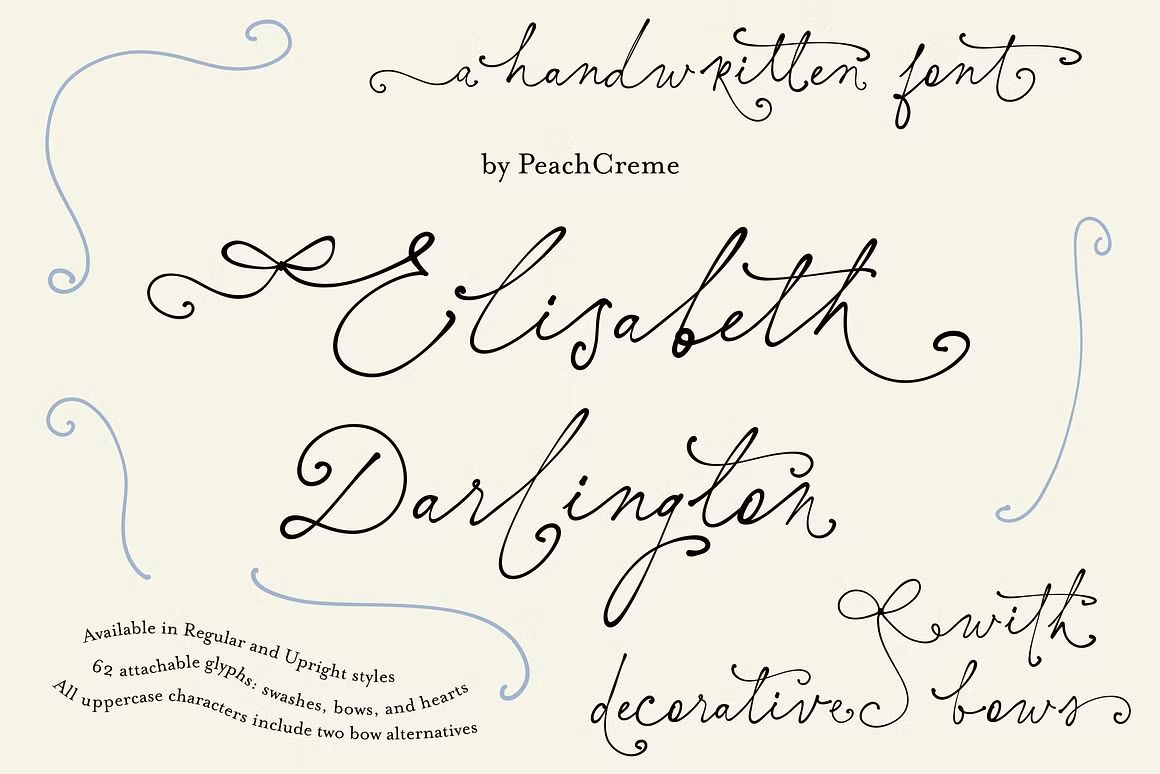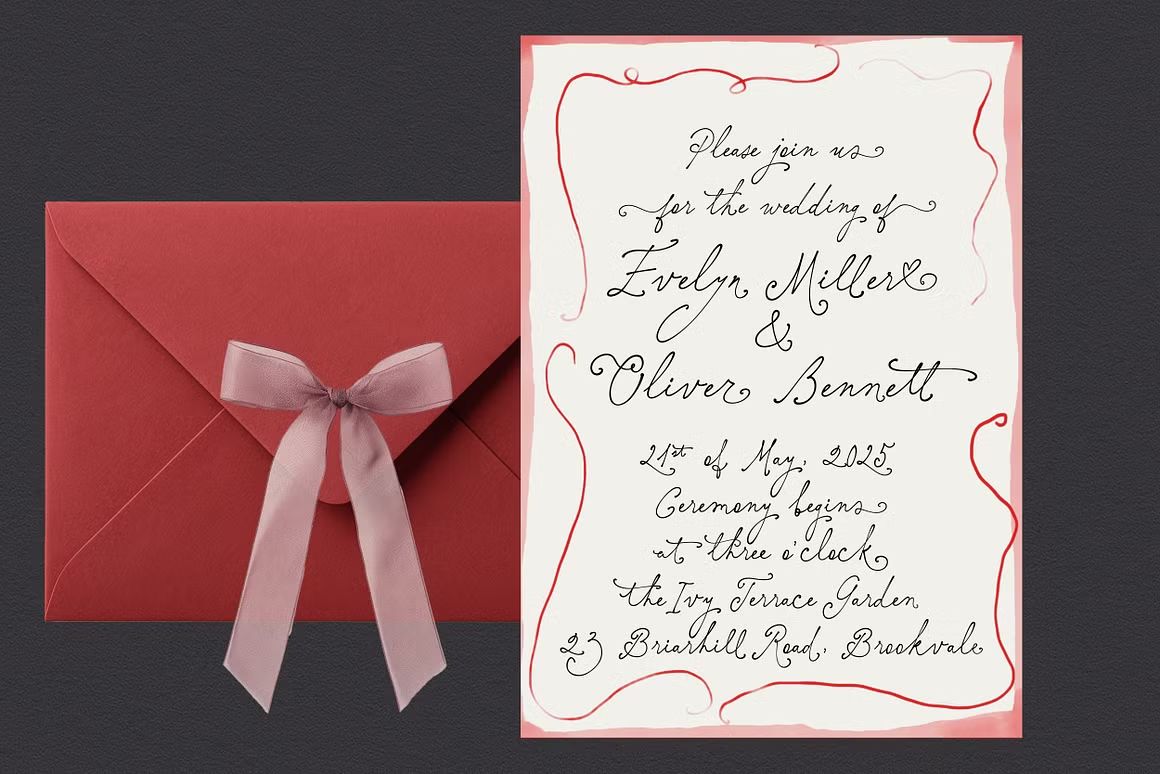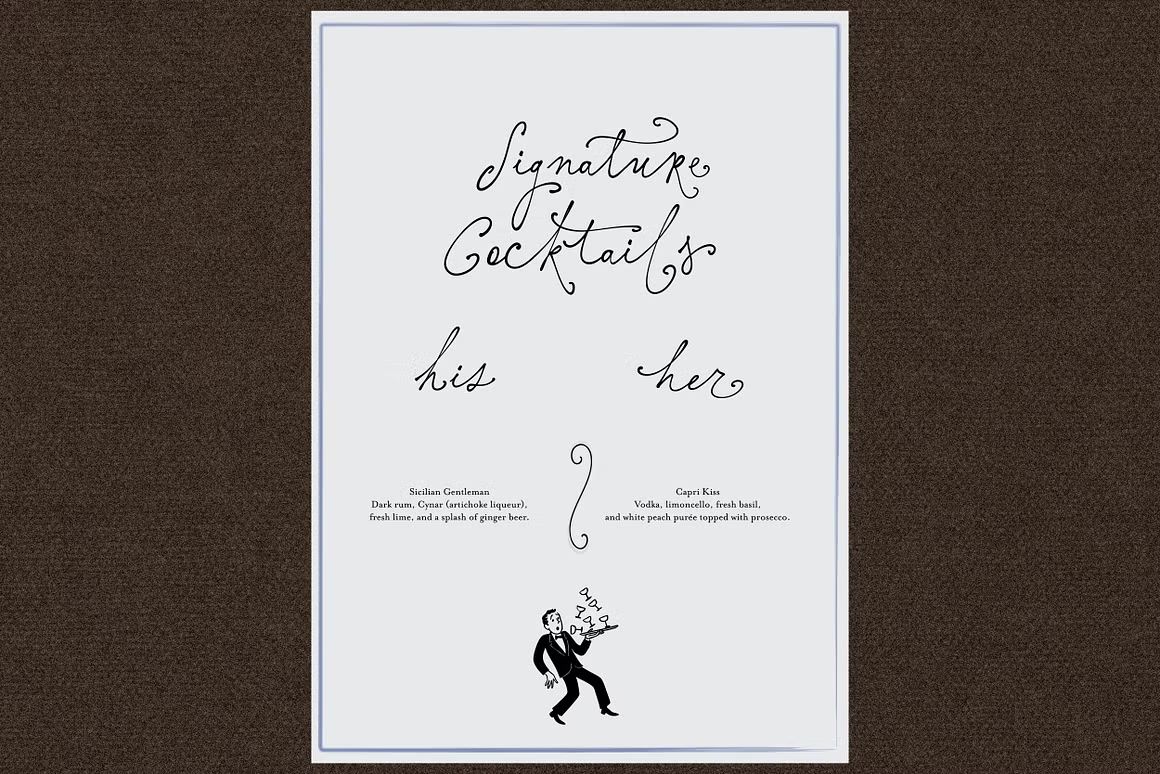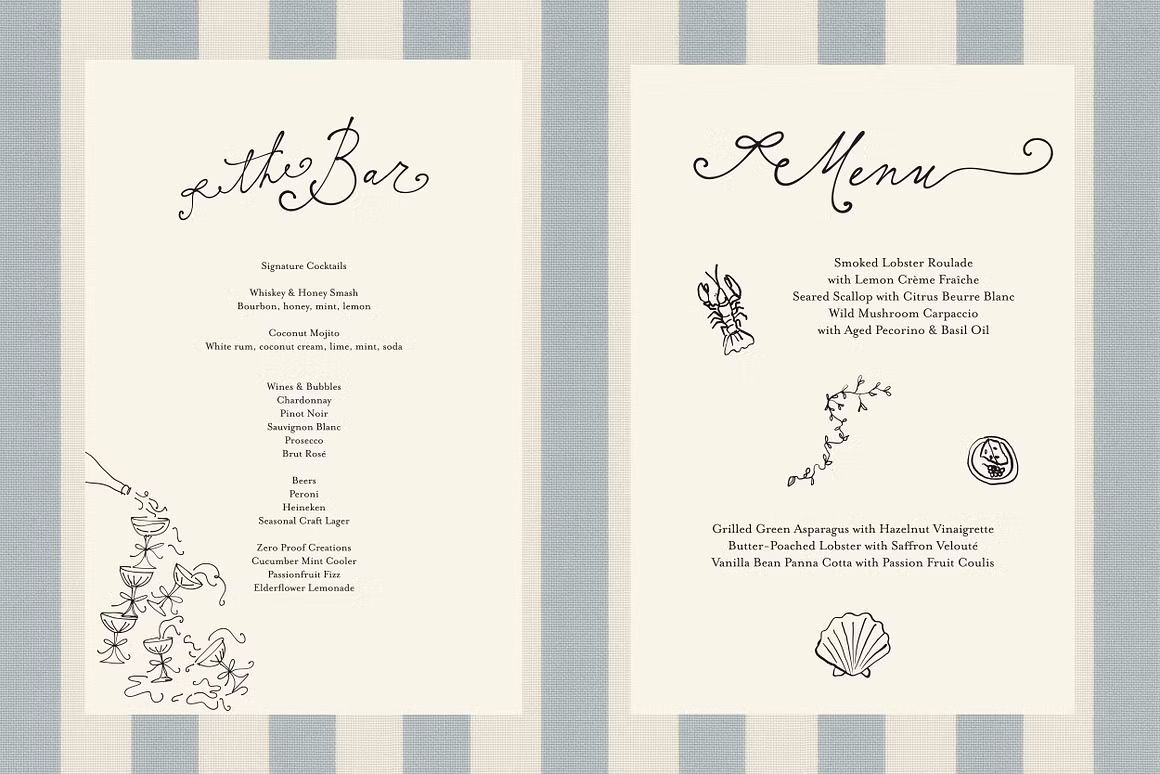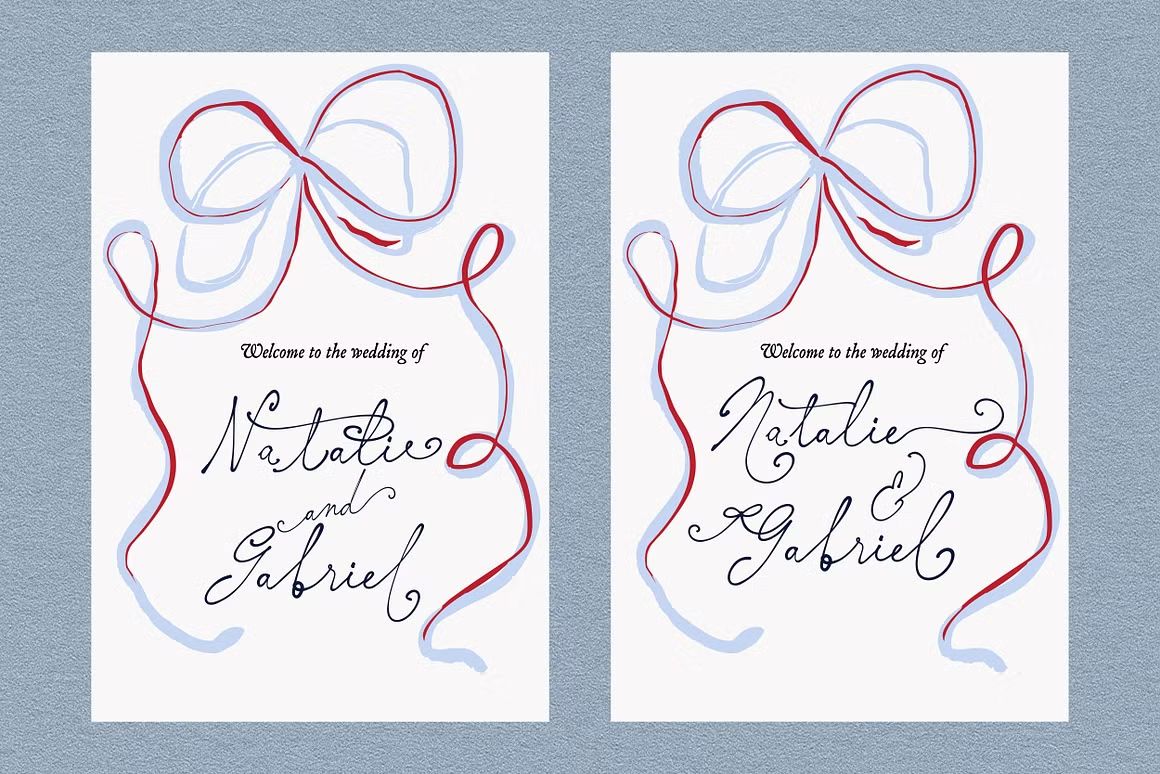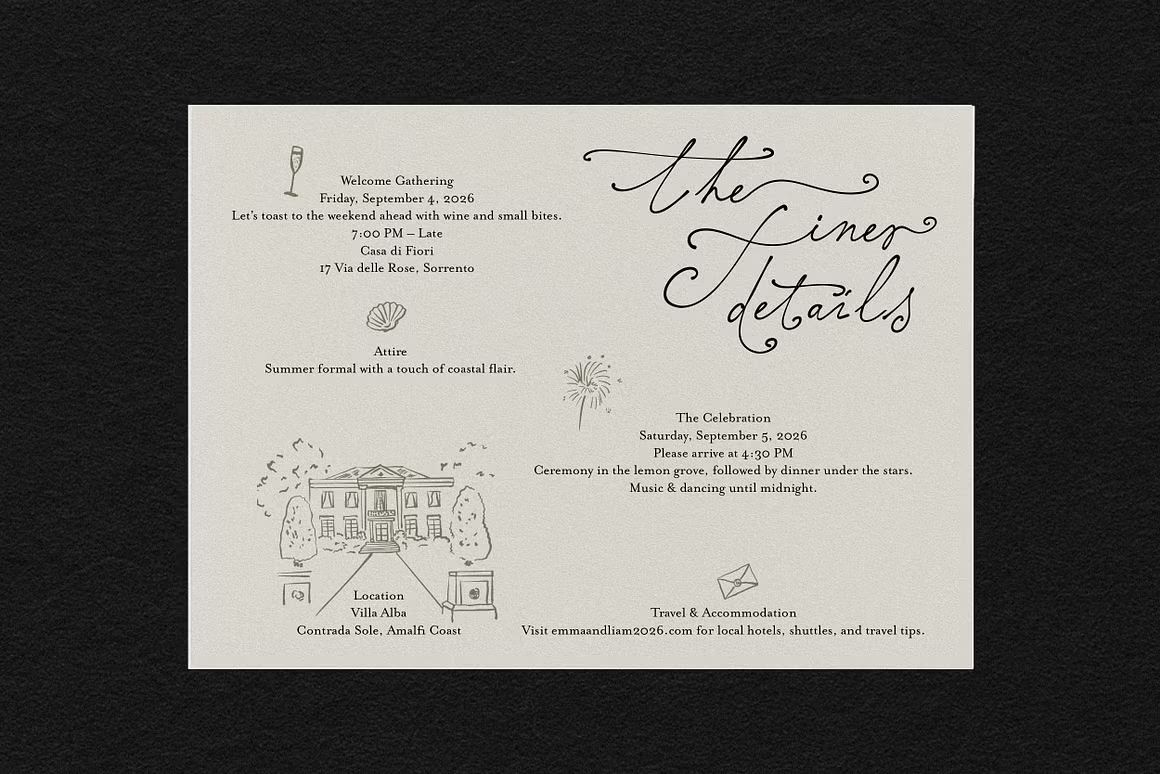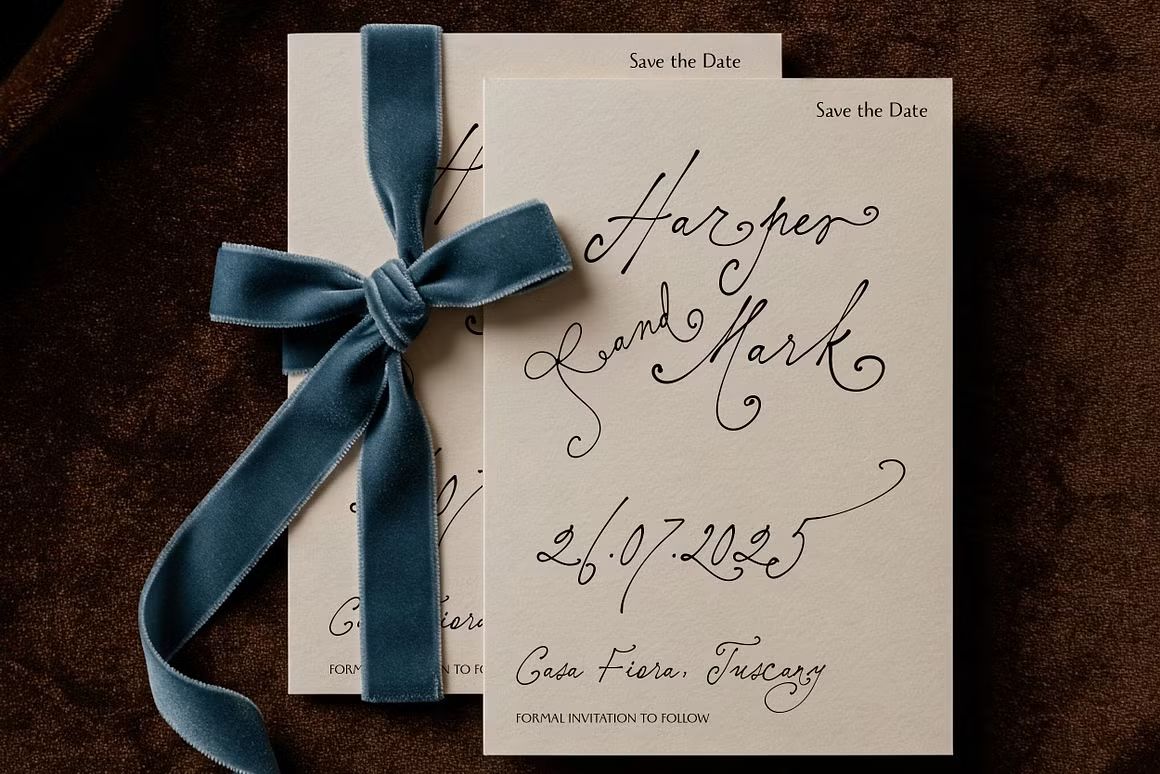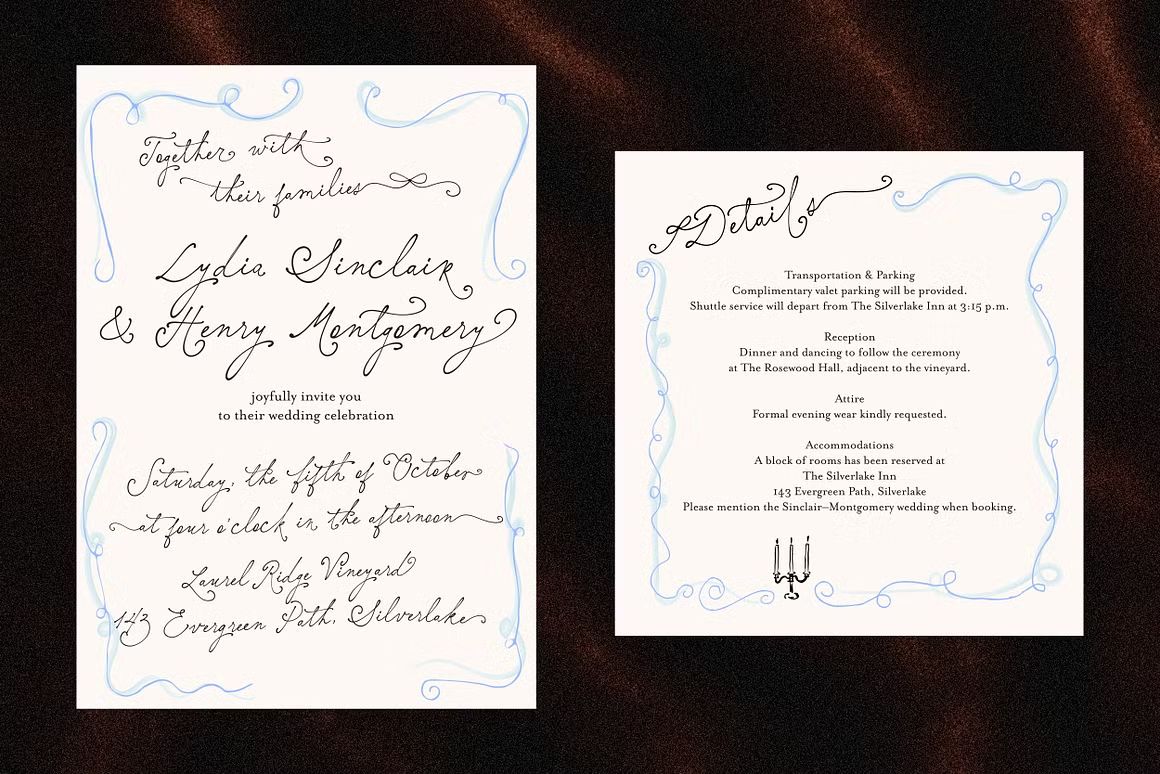
Elisabeth Darlington – Script Font
Elisabeth Darlington adalah font script bergaya kaligrafi klasik yang elegan dan mewah. Cocok untuk wedding, logo, dan desain feminin. Format OTF/TTF/WOFF, siap digunakan.
Elisabeth Darlington adalah font script elegan bergaya klasik dengan lekukan halus dan nuansa mewah. Didesain menyerupai tulisan tangan kaligrafi, font ini sangat cocok untuk undangan pernikahan, logo brand premium, kemasan produk, dan desain editorial. Karakternya yang anggun dan feminin memberikan kesan romantis dan profesional dalam setiap tampilan. Kompatibel dengan berbagai platform desain modern.
• Gaya script kaligrafi dengan lekukan anggun
• Ideal untuk wedding, branding mewah, dan editorial
• Termasuk huruf besar, kecil, angka, simbol, dan ligatur